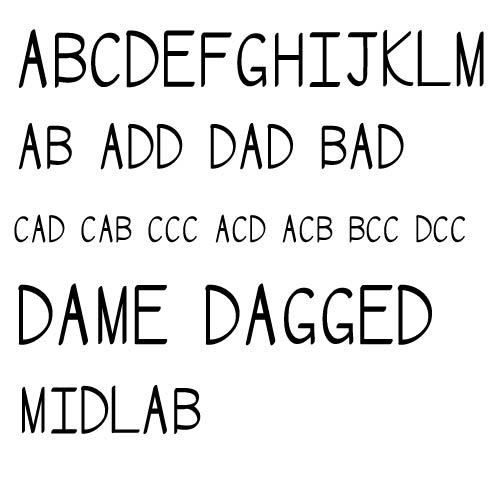
เหมือนกับของแมคและห้าโอ
ล้มเลิกโครงการ ForWhat
ลบ EVOLUTION และ HangBaan เพราะดูทุเรศลูกตา + ไม่ได้จัดช่องไฟเหวอะไรเลย
เตรียมโปรเจคท์ใหม่ BonJang (บรรจง)
ป.ล. 5 บรรทัดบนเป็นฟอนต์ผมครับ
ลบทำไมครับ?
จริงๆ แล้วอัพเกรดได้นะ
แต่ไม่แนะนำให้ลบเลย
เพราะมันเป็นตัวชี้ให้เห็นถึงพัฒนาการของเรา
ฟอนต์ใหม่แทนตัวเก่าที่ถูกผมทิ้ง
เห็นได้ชัดว่าในนี้ ตัวหนังสือยังบิดเบี้ยว บรรทัดก็ไม่เท่ากัน แต่ช่องไฟผมปรับให้เท่ากันทุกตัวแล้ว - กำลังทำการแก้ไขอยู่ครับ
อยากให้ทุกคนทำระบบสกุลฟอนต์ของตัวเองเลยครับ
ผมว่ามันน่าจะน่าสนใจดีในการเก็บประวัติ
(หรือไม่ก็อาจจะทำเว็บพอร์ทสำหรับฟอนต์เราเลยก็ได้ อันนี้ก็ไม่แน่)
เอาไปใส่ในพอร์ทที่กำลังคิดทำอยู่
ตอนนี้กำลังวางแผนในการทำฟอนต์ลับๆอยู่
ทำไว้หลายๆตัว ต่อไปเอาเข้าพอร์ทโลด
BonJang อ่านว่า บอนแจง ไปแล้วอะ
BunJong ?
จริงด้วยสิ
บอนจัง บันจอง
ฟอนต์ตูชื่อ sp digit ไม่ใช่ sm digit  :05: